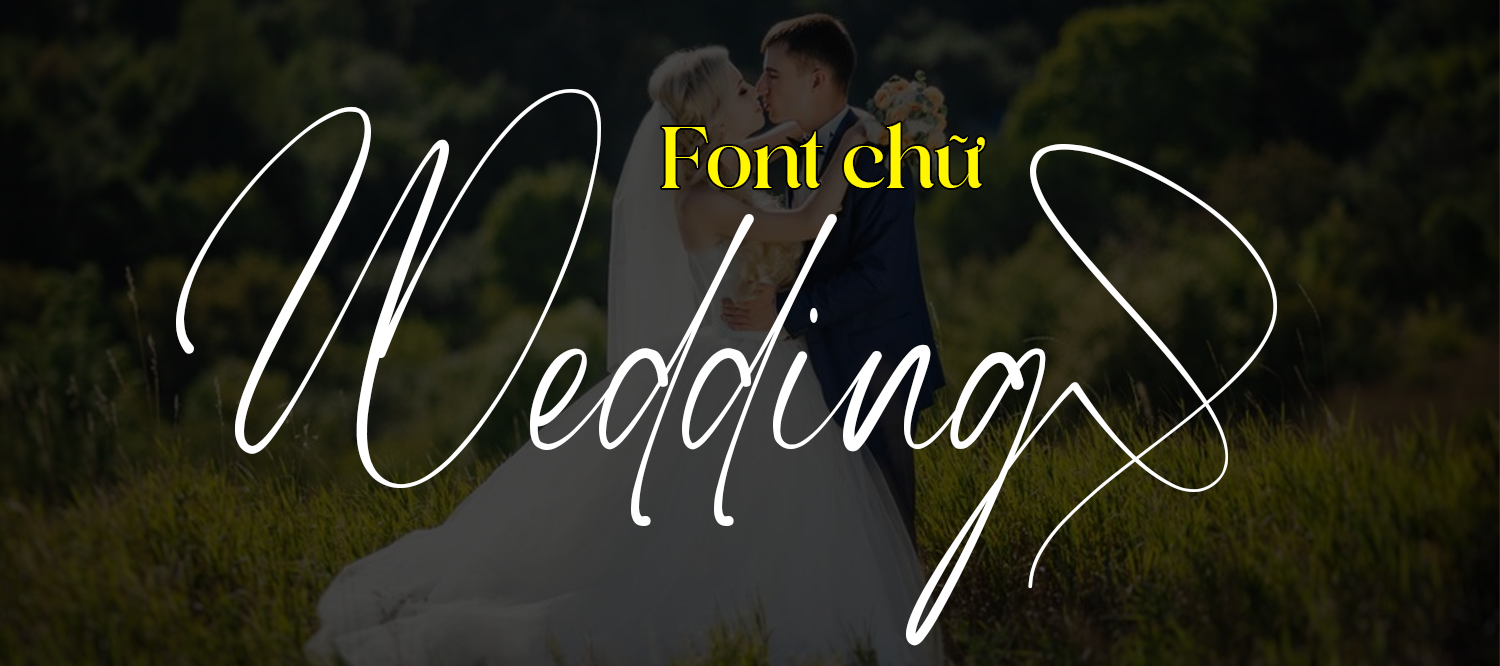
Tìm hiểu về font chữ Wedding - Lựa chọn hoàn hảo cho ngày cưới
Font chữ là một yếu tố quan trọng không thể thiếu trong bất kỳ thiết kế nào, đặc biệt là trong các dự án liên quan đến ngày cưới. Font chữ Wedding không chỉ đơn giản là các ký tự ghi chép mà nó còn mang đến sự lãng mạn, sang trọng và phong cách riêng biệt cho các ấn phẩm như thiệp cưới, bảng chào mời, đồ trang trí và hơn thế nữa. Để tìm hiểu thêm về các loại font chữ Wedding phổ biến và cách chọn lựa chúng, hãy cùng khám phá qua bài viết này.
Tại sao font chữ là yếu tố quan trọng trong thiết kế cưới?
Font chữ Wedding không chỉ đơn giản là công cụ để truyền tải thông tin mà nó còn đóng vai trò quan trọng trong việc tạo nên sự đặc biệt và độc đáo cho mỗi dự án thiết kế cưới.
• Font chữ chính là cách để cặp đôi thể hiện phong cách và cá tính của mình thông qua thiệp cưới và các vật phẩm trang trí. Với sự đa dạng của các loại font từ cổ điển đến hiện đại, từ nữ tính đến trang nhã, font chữ giúp các đôi uyên ương lựa chọn phong cách mà họ muốn gửi gắm vào ngày trọng đại của mình.
• Font chữ không chỉ đơn thuần là hình thức mà nó còn là cách để truyền tải cảm xúc và tình cảm. Những nét chữ viết tay ấm áp có thể tạo ra một cảm giác gần gũi và thân mật, trong khi những font chữ serif hoặc cổ điển có thể mang đến sự lịch sự và trang trọng.
• Việc lựa chọn font chữ phù hợp cũng giúp đảm bảo sự hài hòa và đồng nhất trong thiết kế tổng thể của đám cưới, từ thiệp mời đến bảng chào mời và các vật phẩm trang trí khác. Một font chữ được lựa chọn và sử dụng một cách thích hợp cũng có thể thể hiện sự chuyên nghiệp và chuẩn mực trong tổ chức và lên kế hoạch cho một sự kiện đám cưới.
Các kiểu font chữ Wedding phổ biến trong thiết kế cưới
Như đã nói, các loại font chữ không chỉ đơn giản là phương tiện giao tiếp mà còn là cách để cặp đôi thể hiện phong cách và tạo điểm nhấn cho sự kiện trọng đại của mình. Hãy cùng chúng tôi khám phá những loại font chữ Wedding được sử dụng phổ biến hiện nay.
Font chữ ký viết tay mềm mại SVN-Janelotus
Font SVN-Janelotus là một kiểu chữ ký viết tay mềm mại, với những nét uốn lượn tinh tế và lãng mạn. Nhìn vào đó, bạn sẽ cảm nhận được sự dịu dàng và sự tỉ mỉ trong từng nét vẽ của từng ký tự. Đặc biệt, font chữ này rất thích hợp cho các thiết kế liên quan đến lễ cưới, với khả năng tạo nên không gian lãng mạn, trang nhã và đầy cảm xúc. Những đường nét mềm mại của SVN-Janelotus sẽ làm nổi bật tình yêu và tinh thần trang trọng trong mọi bản thiết kế.
Font chữ Wedding đẹp, viết tay SVN Peristiwa Việt hóa
Font chữ SVN Peristiwa là một lựa chọn tuyệt vời dành cho những ai yêu thích sự tinh tế và cổ điển trong thiết kế viết tay.  Được thiết kế với những đường nét mềm mại, uốn lượn và lãng mạn, SVN Peristiwa không chỉ là một font chữ mà còn là một biểu tượng của sự sáng tạo. Đây là sự lựa chọn hoàn hảo cho các dự án đòi hỏi sự sang trọng như thiệp mời đám cưới, nơi nó thể hiện được sự tinh tế và nét đẹp truyền thống.  Ngoài ra, SVN Peristiwa cũng thích hợp cho các thiết kế hiện đại như logo trang web, nơi nó mang đến sự độc đáo và chuyên nghiệp
Font chữ ký viết tay thu hút - Jhodes Việt hóa
Font chữ Jhodes là một lựa chọn hoàn hảo cho những ai yêu thích sự tinh tế và đẳng cấp. Được biến tấu từ chữ ký viết tay, font chữ này mang đến một cảm giác thân thiện và cá nhân hóa đặc biệt. Đường nét của Jhodes được thiết kế mềm mại và phóng khoáng, tạo nên sự kết hợp hài hòa giữa yếu tố hiện đại và cổ điển. Với tính linh hoạt và đa dạng trong ứng dụng, Jhodes phù hợp cho nhiều lĩnh vực từ thương hiệu cá nhân, logo đến thiệp mời và tiêu đề. Đặc biệt, font chữ này còn rất thích hợp để sử dụng trong chữ ký điện tử, mang đến sự chuyên nghiệp và sang trọng cho mỗi thông điệp.
Font chữ viết tay mềm mại TH Orcatlys
Font chữ TH Orcatlys là một thiết kế độc đáo, mang đậm chất chữ ký bằng mực với nét viết đậm nhạt nhẹ nhàng, như những nét cọ nhẹ trên giấy. Với đường nét mềm mại và phóng khoáng, Orcatlys không chỉ đơn thuần là một loại font chữ mà còn là một tác phẩm nghệ thuật đích thực. Sự tinh tế và lãng mạn của font chữ này khiến nó phù hợp với nhiều lĩnh vực, từ thiết kế đồ họa đến các ứng dụng yêu cầu sự trau chuốt và sáng tạo. Orcatlys là sự kết hợp hoàn hảo giữa nét cổ điển và hiện đại, mang đến sự sang trọng và độc đáo cho mọi dự án thiết kế.
Wellyon Regular - font chữ Wedding đẹp ấn tượng
Font chữ Wellyon Regular mang đậm phong cách viết tay, với nét đẹp ngọt ngào và mềm mại. Được Việt hóa bởi S99.VN, font chữ này mang đậm chất lãng mạn và trang nhã, hoàn hảo cho các thiết kế thiệp cưới hoặc các dự án liên quan đến ngày trọng đại của bạn. Với từng nét chữ uốn lượn tinh tế, Wellyon Regular không chỉ là sự lựa chọn hoàn hảo để tôn vinh những khoảnh khắc đẹp trong cuộc đời mà còn là biểu tượng của sự trang trọng và sự kiêu sa trong mỗi chi tiết thiết kế.
Font chữ ký mềm mại viết tay SVN-Pateglamt Script